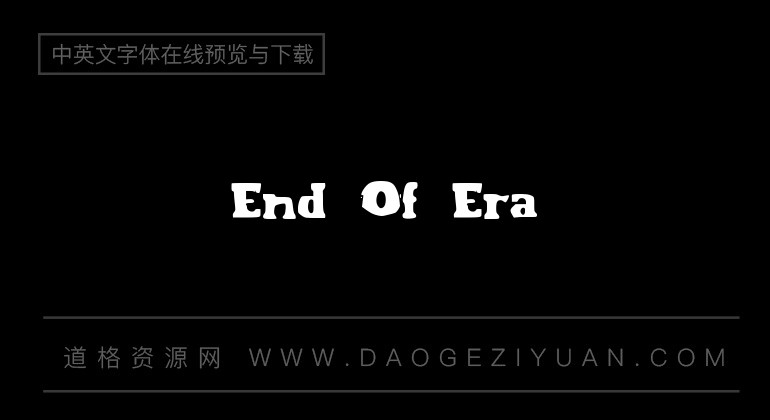
End Of Era 是一款手写风格的英文字体,由 Brian J. Bonislawsky 创作于 2014 年。这款字体的风格充满了浓郁的怀旧和复古气息,仿佛带着一种历史感。它的字形较为简单,笔画流畅,整体来说非常易于阅读。 End Of Era 字体适用于各种设计场景,如海报、书籍封面、标志设计等。它可以为设计师们带来一种独特的视觉效果,使得所设计的作品更具有艺术感和个性化。 此外,End Of Era 字体还包含了多种字形变体和 OpenType 功能,这些功能可以帮助设计师们创造出更为丰富多彩的设计效果。内容介绍
End Of Era是一款非常不错的手写艺术字体,具有很好的视觉感,适合于文化类的宣传设计、商业类品牌的广告和产品包装设计以及个性化文字排版等较多场景。